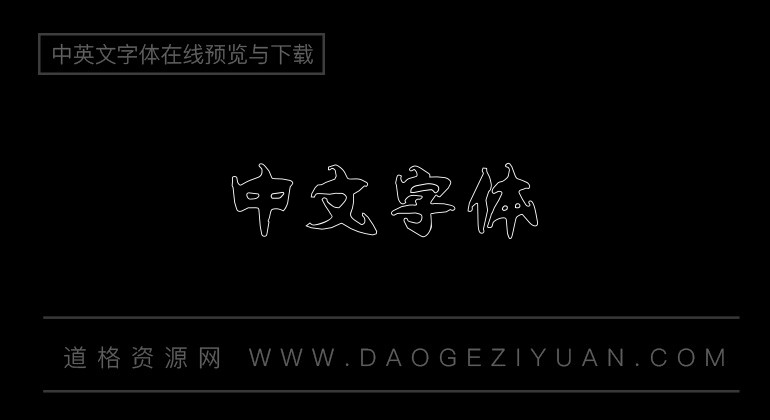
腾祥倩心简是一款由腾祥字体设计团队设计的简体中文字体,它以简单的线条和曲线组成,给人以清新、活泼的感觉。它的字体风格独特,给人以温暖、柔和的感觉,让人们在阅读文字时感到舒适。腾祥倩心简字体具有良好的可读性,可以用于报纸、书籍、杂志、网页等多种媒体中。文件名:TengXiangXinJian-1.ttf
腾祥倩心简是一款非常不错的手写艺术字体,具有很好的视觉感,适合于文化类的宣传设计、商业类品牌的广告和产品包装设计以及个性化文字排版等较多场景。